Как сохранить различимость строчной «э» в рукописном шрифте
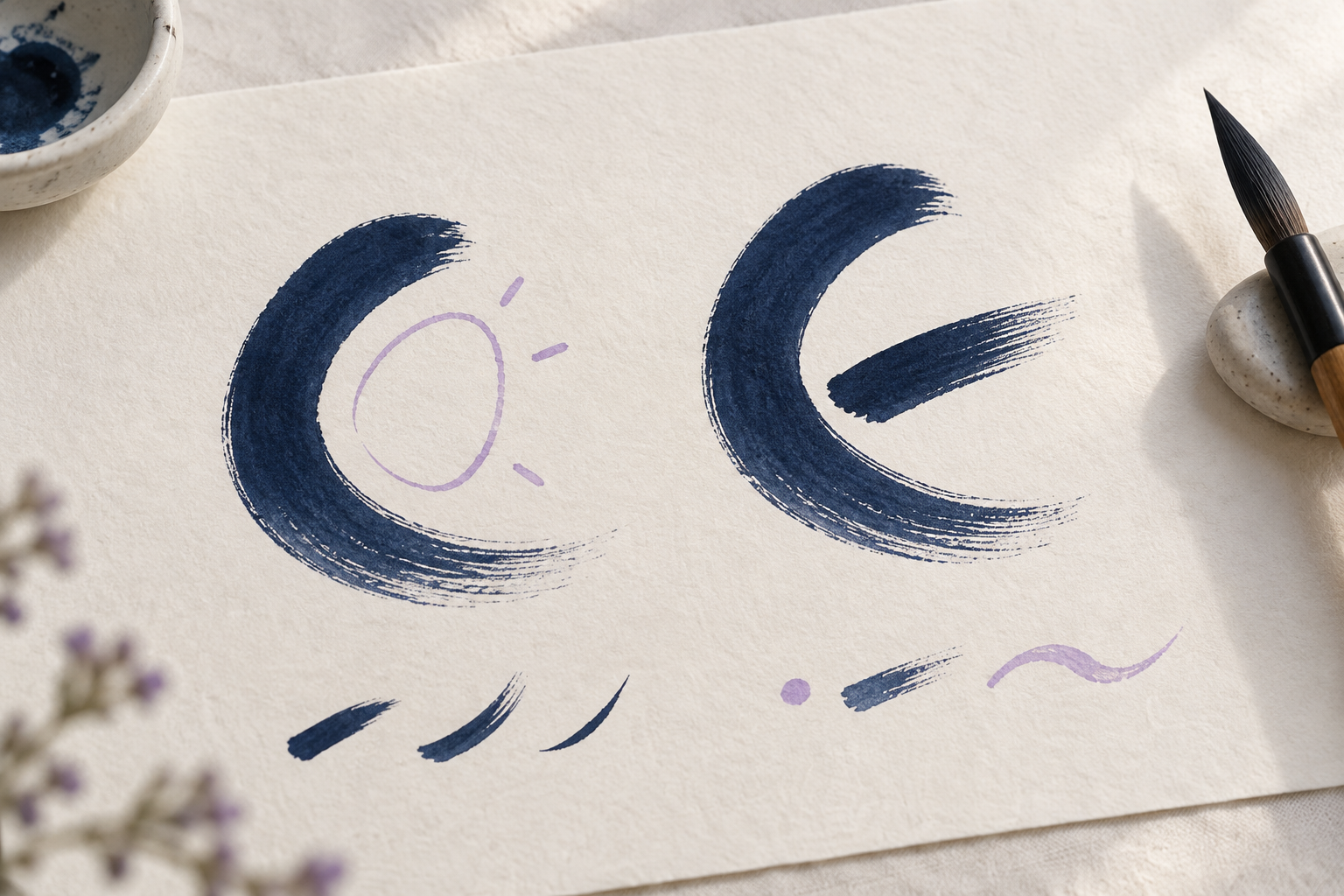
Строчная «э» остаётся узнаваемой, когда читатель сразу видит открытое направление её корпуса и короткую поперечную черту внутри. В рукописном шрифте эти признаки легко теряются: дуга закрывается, черта сливается с соединением или исчезает при уменьшении. Разберём, как построить форму, проверить её рядом с «с» и оценить в словах, не превращая авторский почерк в механический знак.
Из чего складывается узнаваемая «э»
У строчной «э» есть три опорных признака: открытый корпус, направленная внутрь поперечная черта и внутренний просвет. В печатной форме эти детали разделены достаточно ясно, но при письме от руки они зависят от одного движения пера. Поэтому полезно сначала нарисовать знак отдельно и проверить его силуэт, а уже потом добавлять вход и выход для соединения.
Сравните буквы «с» и «э» не по названию, а по тому, как они устроены. У «с» открытая дуга сама задаёт форму: внутри нет дополнительной черты. У «э» эта черта пересекает часть корпуса и меняет направление чтения. Если её убрать, укоротить до почти незаметной царапины или случайно продолжить за контур, знак может выглядеть как «с» с помаркой. Если же черта слишком длинная и тяжёлая, она начинает спорить с дугой.
В рукописном начертании не обязательно копировать печатный рисунок буквально. Можно сохранить ритм почерка, наклон и характер соединений, но отличительные детали должны быть устойчивы от экземпляра к экземпляру. Один красивый образец ещё не гарантирует, что буква будет читаться в слове: важна повторяемая конструкция.
Сначала выберите каркас, затем добавьте соединения
Начните с корпуса без входного и выходного штрихов. Нарисуйте несколько вариантов дуги одинаковой высоты: более округлый, вытянутый по горизонтали и немного наклонённый в сторону письма. У каждого варианта отметьте место открытия и проведите поперечную черту одним движением. Сравните не отдельные линии, а общий силуэт на расстоянии вытянутой руки.
Рабочая последовательность такая:
- Задайте общую высоту строчных и базовую линию, чтобы «э» не выпадала из строки.
- Нарисуйте открытую дугу и оставьте заметный просвет у её концов.
- Проведите внутреннюю черту через характерную часть корпуса, сохраняя её направление и длину.
- Добавьте вход и выход так, чтобы они не закрывали просвет и не продолжали черту случайным хвостом.
- Повторите знак несколько раз подряд и сравните, какие детали сохраняются без сознательной коррекции.
Не стремитесь на первом шаге сделать движение максимально быстрым. Сначала закрепите конструкцию в медленном темпе, затем ускоряйтесь и наблюдайте, какой признак пропадает первым. Если при обычной скорости систематически исчезает поперечная черта, дело не в недостатке аккуратности: форму следует упростить или изменить траекторию.
Как выбрать длину и положение поперечной черты
Поперечная черта должна восприниматься частью «э», а не отдельным штрихом, который случайно пересёк дугу. Слишком короткая черта выглядит как точка или неровность; чрезмерно длинная делит букву пополам и может создавать впечатление, что внутри корпуса находится другой знак. Начните с умеренной длины, затем сделайте рядом два крайних варианта: заметно короче и длиннее. Разница станет понятнее, когда вы сравните их в словах.
Важно и место, где черта входит в корпус. Если вести её близко к верхнему краю, знак может потерять привычную опору и смотреться как декоративная завитушка. Слишком низкое положение уменьшает нижнюю часть просвета. Практическое правило — выбрать точку, которую легко воспроизводить в вашем движении, а затем следить за одинаковым отношением черты к высоте буквы, а не за измерением миллиметров.
Учитывайте направление пера. При плавном движении черта может естественно продолжать дугу, но если перо резко меняет скорость, появляется утолщение или клякса. В обычном письме это допустимая особенность почерка, однако в шрифте повторяющееся утолщение превращается в постоянную деталь. Проверьте, не делает ли соединение точку пересечения визуально тяжелее остальной буквы.
Просвет важнее декоративной точности
Читатель узнаёт форму через соотношение чёрного штриха и свободного пространства. Если отверстие у «э» почти закрыто, внешний контур становится похож на овал; если внутренний просвет тесен, поперечная черта сливается с дугой. Поэтому после каждого изменения смотрите не только на линии, но и на белые участки: открыт ли проход между концами корпуса, не зажат ли внутренний промежуток, не образовалась ли тёмная масса в точке пересечения.
Уменьшите рисунок или отойдите от листа. На крупном образце легко различать тонкую черту и сложное соединение, которые пропадают в небольшом кегле. В уменьшении у «э» всё ещё должны угадываться открытый корпус и внутреннее направление. Если остаётся только дуга, сначала увеличьте ясность признака, а уже потом возвращайте изящные детали.
Ориентируйтесь на собственный рабочий диапазон размеров. Не существует универсального числа, при котором любая рукописная буква становится нечитаемой: результат зависит от толщины штриха, контраста, расстояния между знаками и конкретного рисунка. Используйте пробный набор в том размере, где шрифт действительно будет применяться, и проверьте также печать или экран, если это ваши целевые носители.